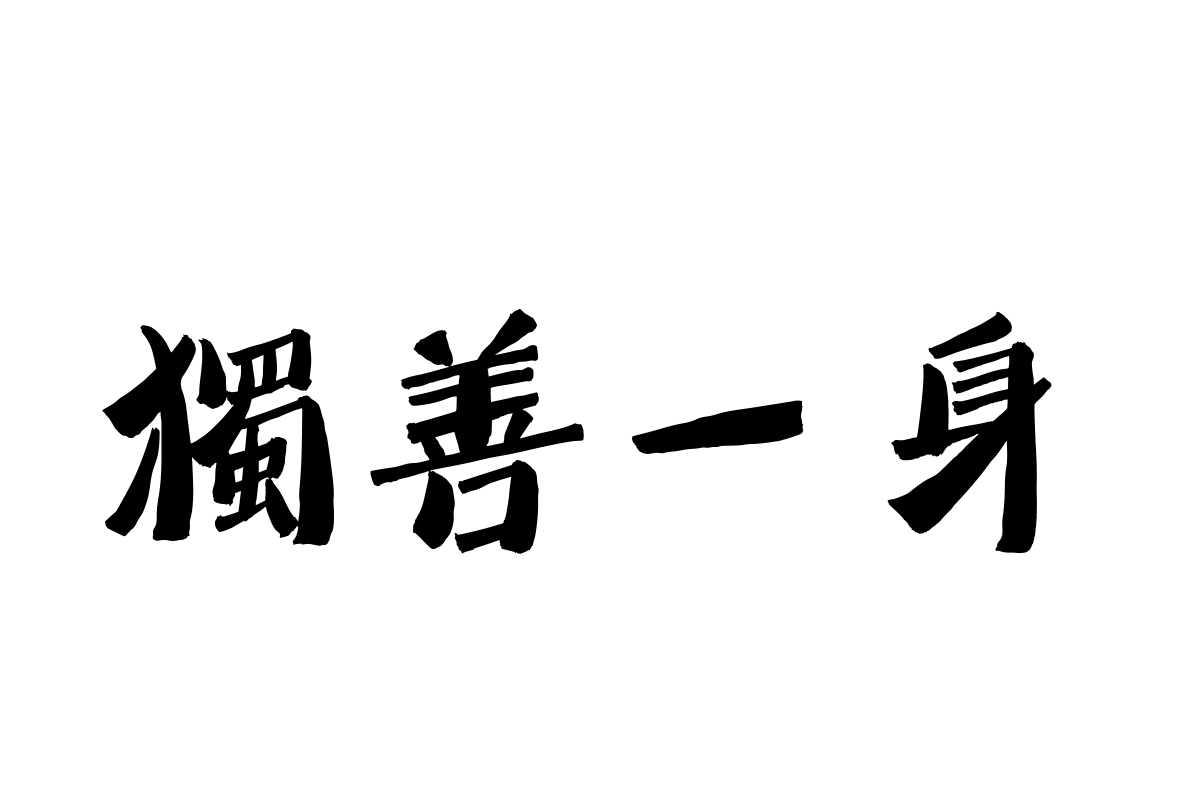
汉仪迪升春山体是一款具有独特风格的中文字体,它以简洁明快的风格赢得了广大用户的喜爱。这款字体的设计灵感来源于春天的山峦,通过巧妙的笔画组合和结构布局,展现出了春天生机勃勃的气息。
汉仪迪升春山体的特点主要体现在以下几个方面:
1. 字形设计独特:汉仪迪升春山体的字形线条流畅,结构紧凑,给人一种简洁明快的感觉。同时,它的笔画粗细变化也恰到好处,既保持了整体的协调性,又不失个性。
2. 风格清新自然:这款字体采用了简洁明快的设计风格,使得整个文字呈现出一种清新自然的气息。无论是用于标题、正文还是广告宣传等场合,都能让人感受到春天的美好气息。
3. 适用范围广泛:汉仪迪升春山体适用于各种类型的文本,包括报纸、杂志、书籍、广告、海报等。它的通用性强,能够满足不同场景的需求。
总之,汉仪迪升春山体是一款具有独特风格的中文字体,它以其简洁明快的设计风格和广泛的适用范围,受到了广大用户的喜爱。无论是用于个人项目还是商业用途,都可以考虑使用这款字体来提升整体视觉效果。